可爱字体免费下载大全
在众多字体种类中能够独树一帜、脱颖而出的必须是可爱字体,时常运用在各类广告设计当中。可爱的字体通常造型生动活泼,有鲜明的节奏韵律感,色彩丰富明快,给人以生机盎然的感受,带来视觉的愉悦。今天小编将给大家介绍几款进行挑选的可爱字体,每一款字体设计板式上都凝结了设计师的奇思妙想。
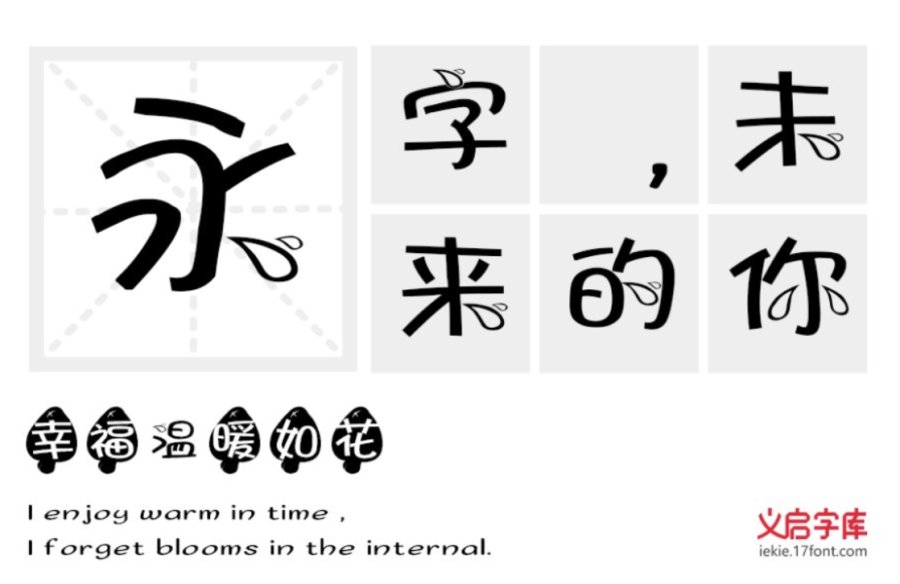
义启蓝瘦香菇体:义启蓝瘦香菇体,灵感来自于广西南宁一小哥失恋后录的一段视频,因为隐约透出的幽默诙谐,在网络上疯狂传播成为了一段时间的热词,这款字体的背景轮廓为香菇的形状图案,所有的点、纳均变为水滴,趣味十足。在增强字体的趣味与辨认度的同时不乏识别字体性,实用性极高。
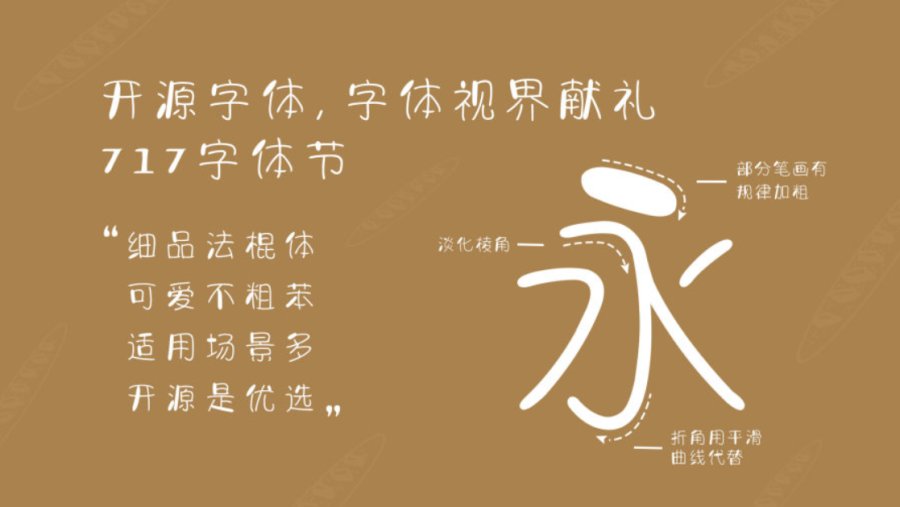
字体视界法棍体:字体视界法棍体由字体视界推出的首款免费字体,它将免费开放商业授权给到所有个人和企业,让所有用户可以免费使用。这款字体灵感来源于香喷喷的法棍面包,把食物的形状以字体的形式呈现,造型新颖。笔画很有规律粗中有细,曲线折角充分展现灵动可爱的气质。
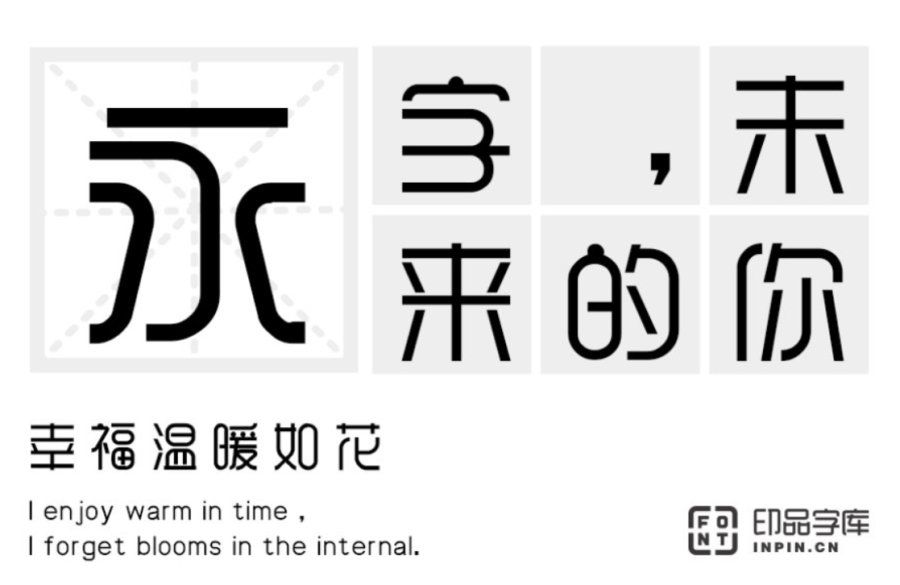
印品雅圆体:设计师对弧形做了内凹外凸的处理,使得笔画更加居中圆滑。表面结构匀称统一,字型做了细致比例的调整易于看图找字,整体观来更加珠圆玉润。加强装饰感的同时,不失俏皮可爱富有的亲和力。